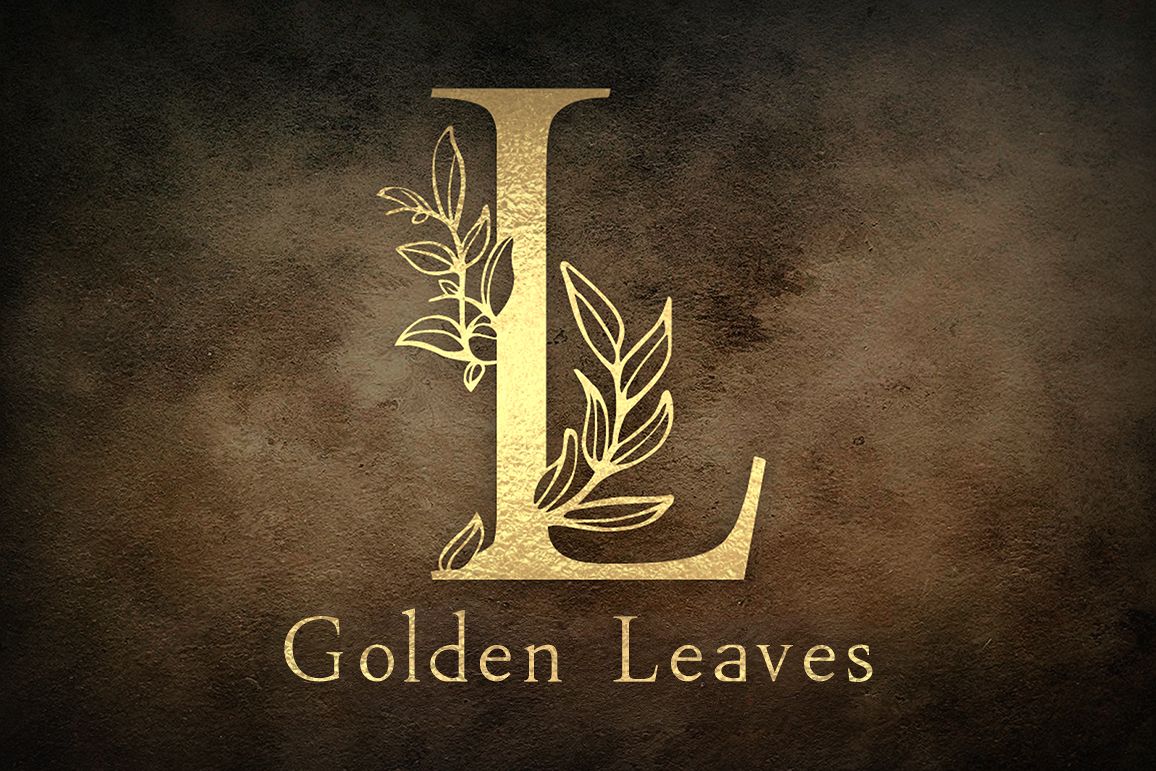
The Golden Leaves
Golden Leaves
Я рад представить «Золотые листья» - стильный шрифт, вдохновленный природой и прошлой осенью. Он идеально подходит для деловых и свадебных открыток, логотипов, брендинга и многого другого, а также для того, чтобы подчеркнуть ваш неповторимый стиль. Особенно хорошо сделать акцент в тексте.
• Цветной шрифт "Golden leaves (SVG)" с текстурой золотой фольги /